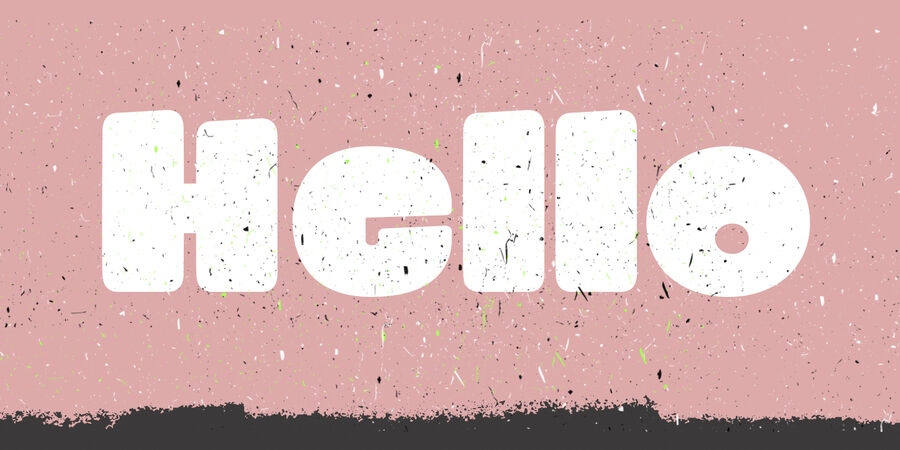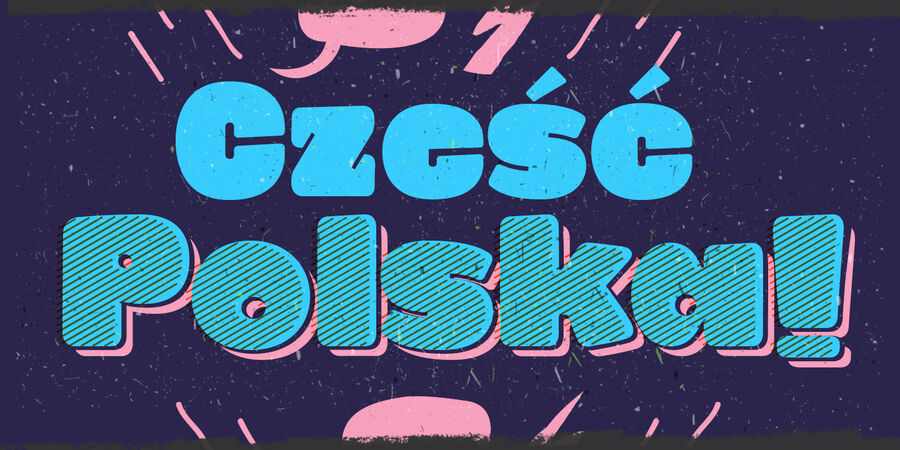
Smile Pro – це наджирний заокруглений грайливий шрифт без зарубок, створений спеціально для дитячих книг, ігор та інших товарів для дітей. Заснований на шрифті Smile 2013 року. Це шрифтовое сімейство містить різні декоративні накреслення, має багатомовну підтримку, включно з кирилицею. Шрифт розробив Родріго Арая Салас та Андрій Кудрявцев у 2015 році.